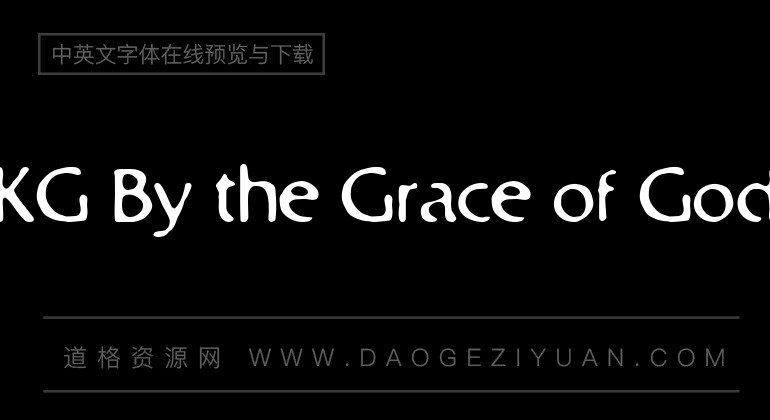
KG By the Grace of God是一款由Katie Guthrie创作的手写体字体。这款字体是一种精细的、可爱的手写体,它充满了温暖和柔和的感觉。它可以用于制作各种各样的设计,比如海报、网站标题、活动标语等,可以为你的作品增添温馨的氛围。此外,KG By the Grace of God还提供了多种字体风格,可以帮助你轻松设计出独特的设计作品。内容介绍
KG By the Grace of God是一款非常不错的手写艺术字体,具有很好的视觉感,适合于文化类的宣传设计、商业类品牌的广告和产品包装设计以及个性化文字排版等较多场景。